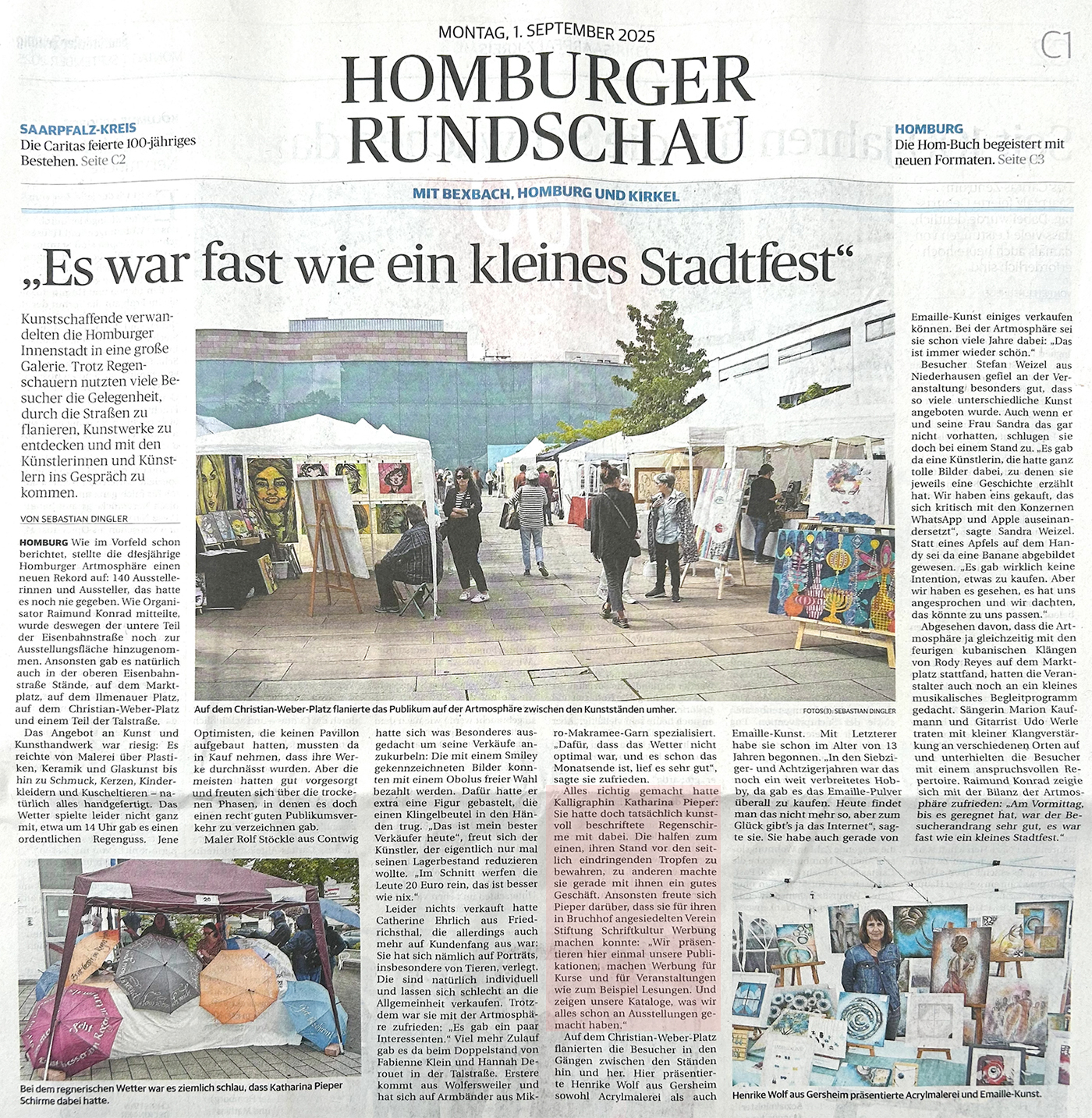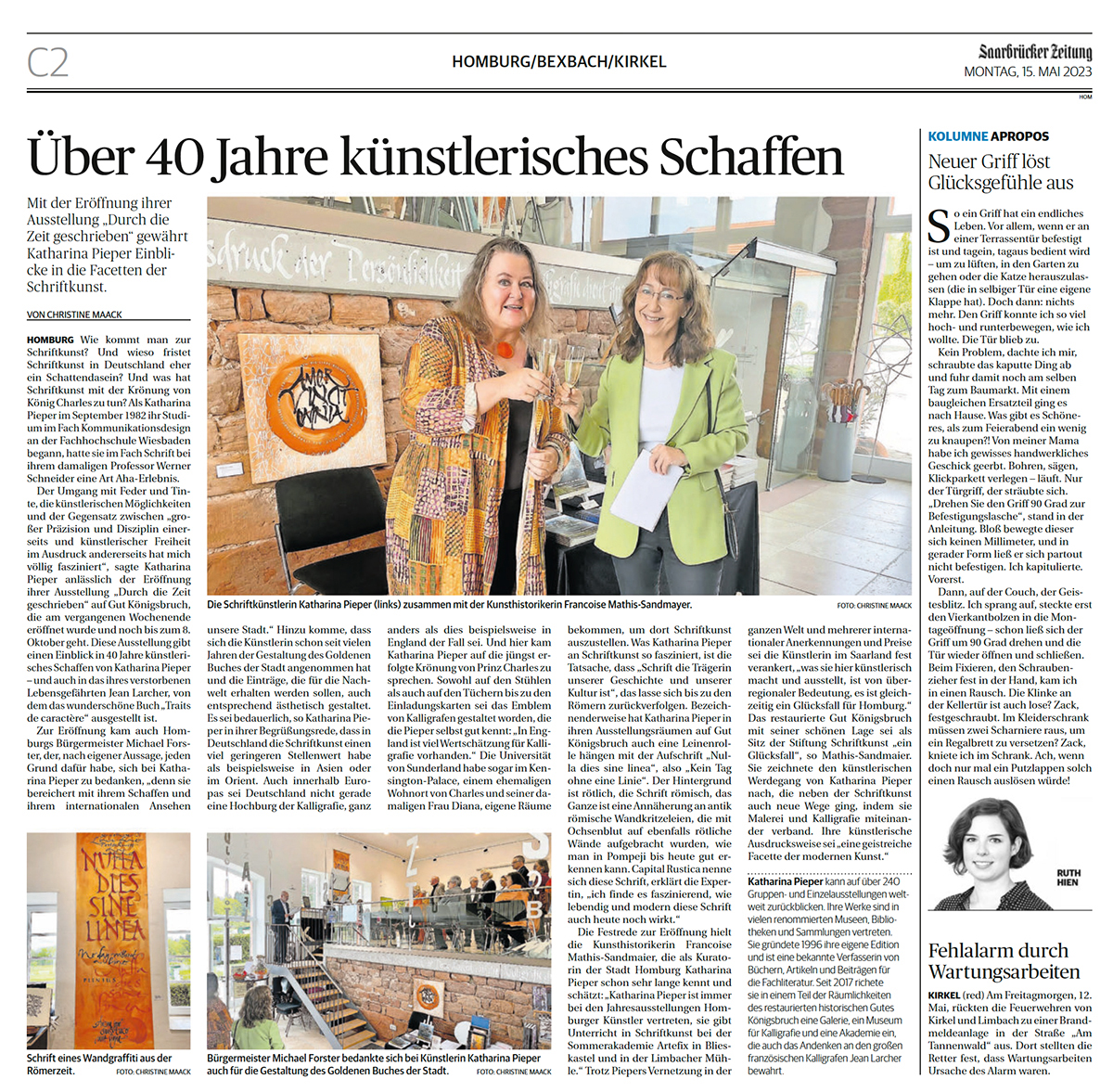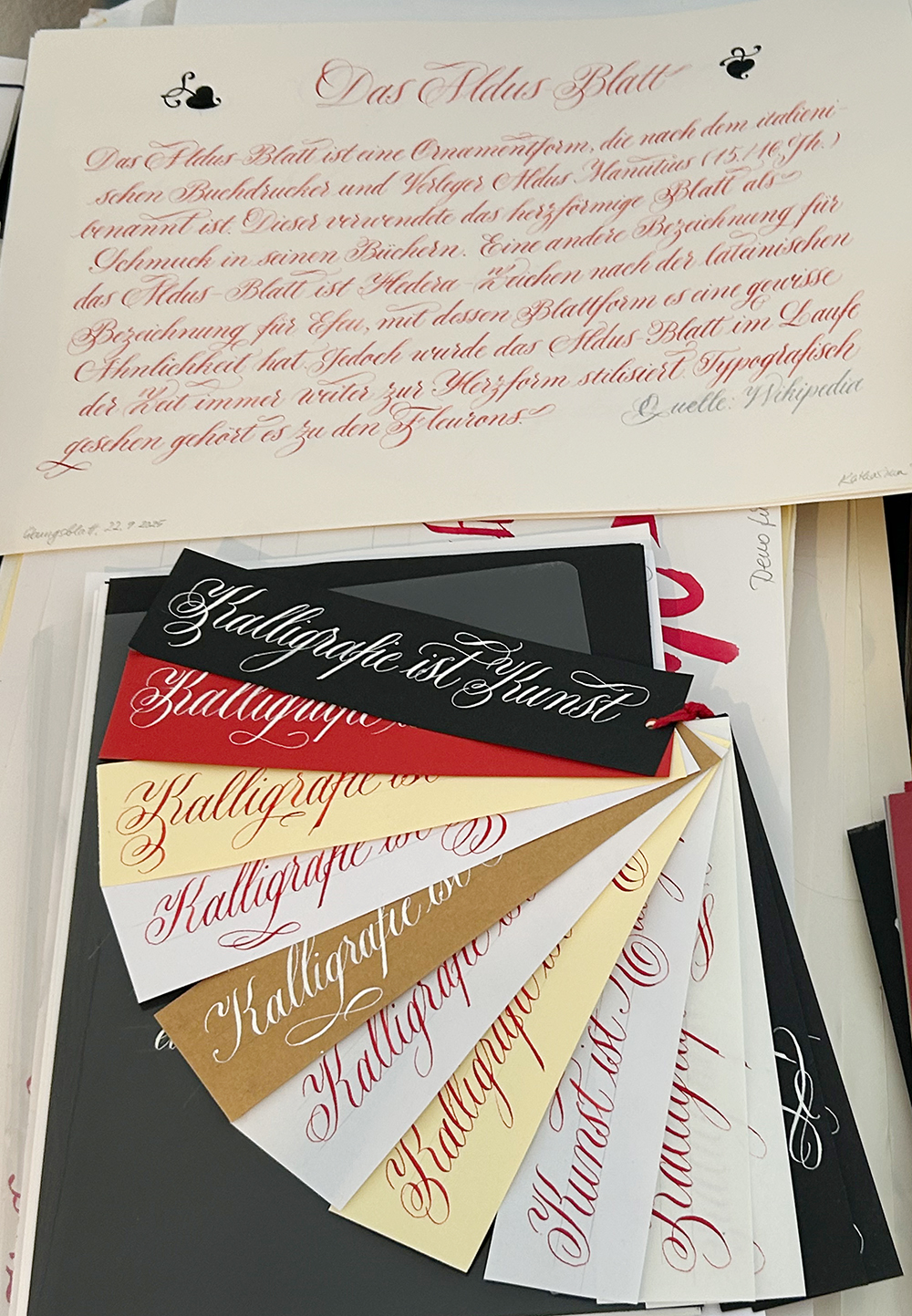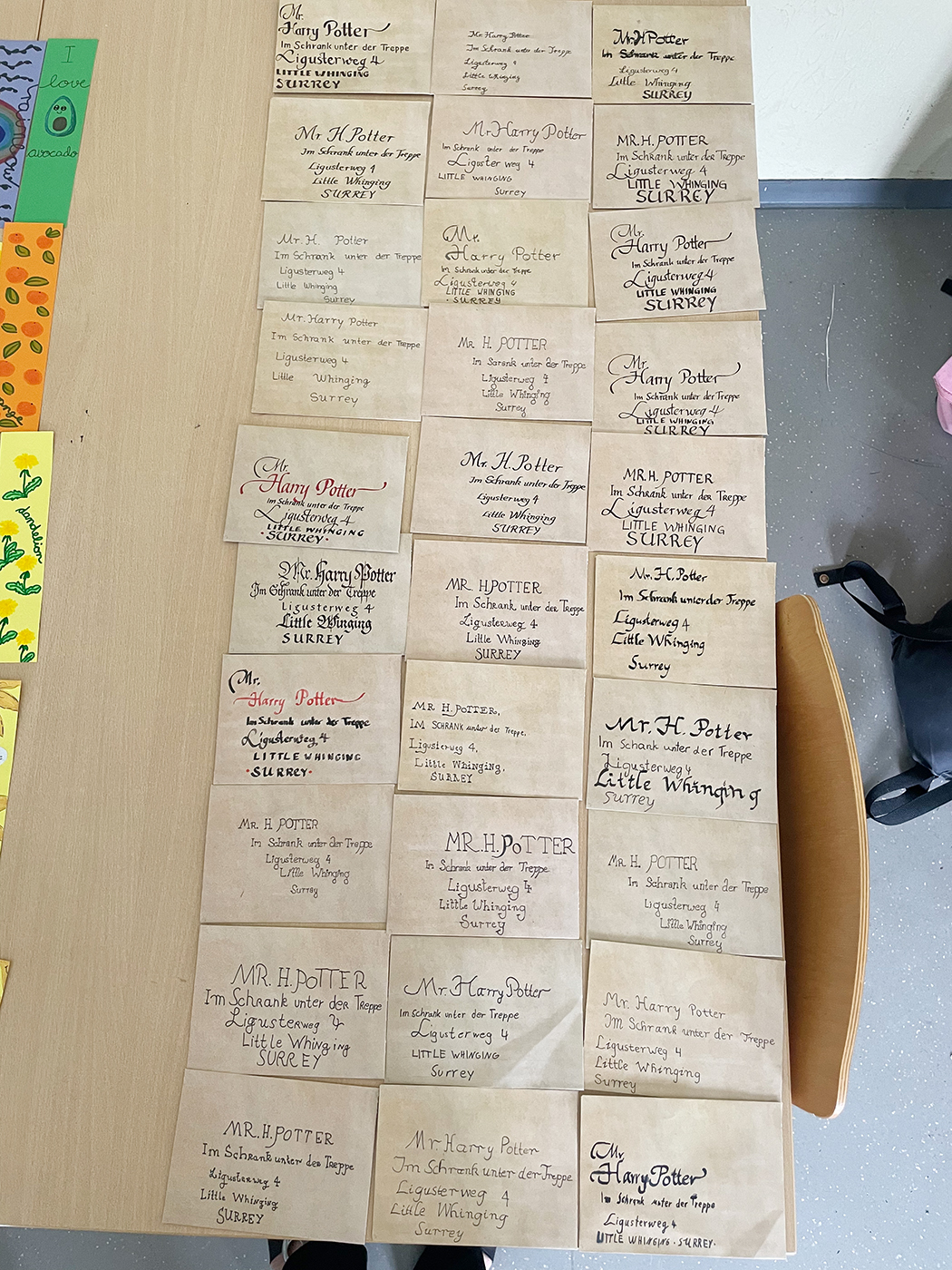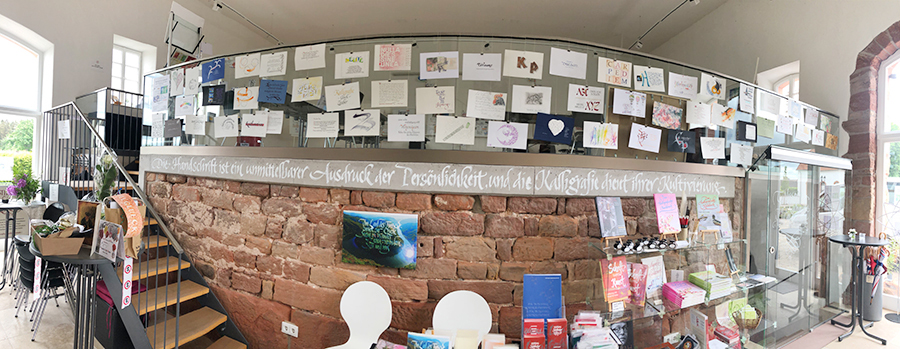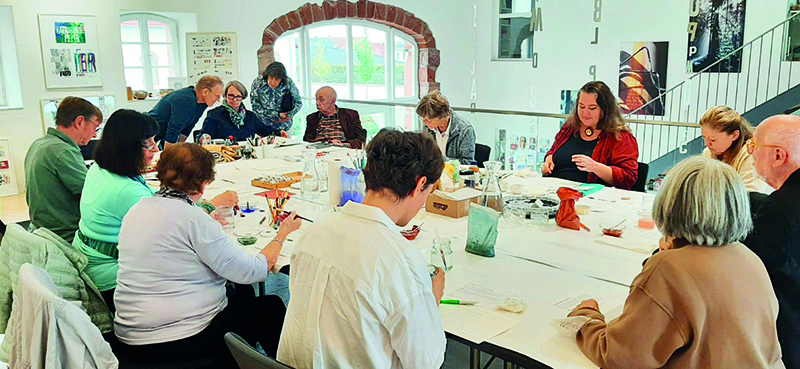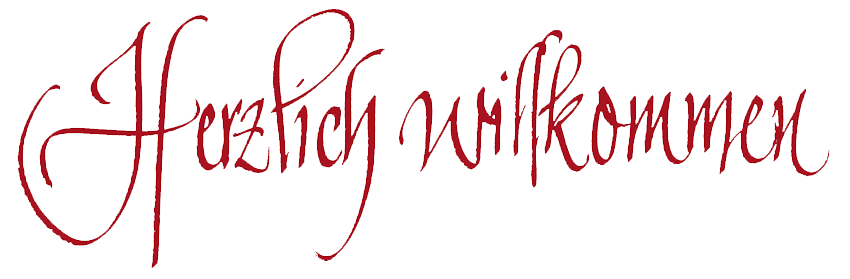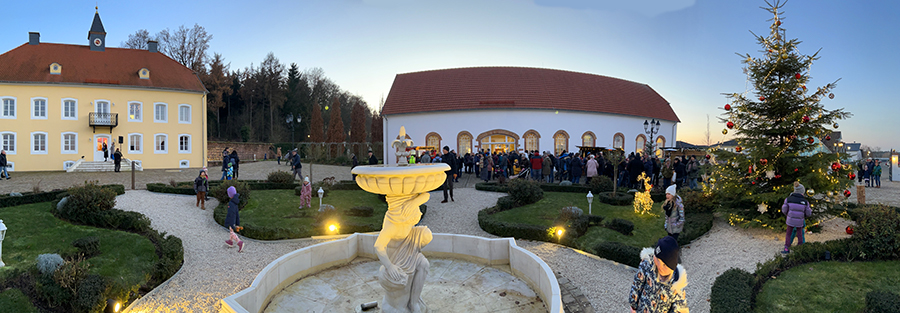
Gegründet im Juli 2016
| Der Verein Stiftung Schriftkultur e. V. wurde 2016 als gemeinnützige Einrichtung gegründet und hat seinen Sitz in Homburg (Saar). Gründerin ist die Schriftkünstlerin, Dozentin, Buchautorin und Dipl.-Designerin Katharina Pieper. Die Stiftung Schriftkultur e. V. versteht sich als eine Institution zur Förderung des Kulturgutes Schrift, der Schriftkunst, der Kalligrafie und der Typografie sowie der Handschrift als Kommunikationsmittel und als Kunstform. Wir organisieren Workshops, Kurse, Seminare und Vorträge, fördern Publikationen und Ausstellungen der Schriftkunst und der Kalligrafie und tauschen uns mit Schriftkünstlern aus aller Welt aus. Wichtig ist der Stiftung Schriftkultur auch, mit Künstlern, Sammlern, Museen, Bibliotheken, Hochschulen, Wissenschaftlern, Gesellschaften und Vereinen in einen Dialog zu treten. Im historischen Gut Königsbruch bei Homburg/Saar, 1766 von Herzog Christian IV. zu Pfalz-Zweibrücken erbaut und von privater Hand aufwendig saniert, hat die Stiftung Schriftkultur e. V. einen passenden Ort gefunden, der eine Galerie, Workshopräume, eine Bibliothek, ein Museum und das Jean-Larcher-Archiv beherbergt. Seit dem Einzug im Frühjahr 2017 finden Workshops, Führungen und Vorträge statt. Im Mai 2018 wurden die Räume mit einer Ausstellung von Katharina Pieper und Jean Larcher eröffnet. Die Stiftung Schriftkultur ist Mitglied im Saarländischen Museumsverband SMV. |
01.06.2026 Das Wochenende vom 30. und 31. Mai stand ganz im Zeichen der Humanistischen Kursive. Sieben Einsteigerinnen und ein Einsteiger widmeten sich unter fachkundiger Anleitung von Katharina Pieper der schönen und eleganten Kursive. Mit Bandzugfeder und viel Elan wurden zunächst die Kleinbuchstaben Schritt für Schritt erarbeitet, bevor es an die neue Formenwelt der Großbuchstaben ging. Alle waren mit viel Begeisterung und Arbeitseifer dabei. Zum Mittagessen brachte jeder etwas Selbstgemachtes mit – dieses Mal ganz besonders feine Delikatessen! Als kleine Abschlussarbeit gestaltete jeder ein Leporello mit einer Zeile eines kurzen Textes. Auf die am Ende präsentierten Ergebnisse waren alle sehr stolz – sie konnten sic wirklich sehen lassen, und das nach nur zwei Tagen Workshop. Vielleicht trug die große Hitze in der Galerie in diesen Tagen dazu bei, dass das Feuer des kalligrafischen Gefechts entfacht wurde und die Feder ihren Tanz über das Papier noch intensiver ausübte! |
01.05.2026 Zwei Tage nach der Ausstellungseröffnung "Im Herz des Friedens – kalligrafische Meditationen" fand in der Galerie der Tag der Kalligrafie für Kinder statt. Von nah, aber auch von fern – aus Saarbrücken, Saarlouis und Kaiserslautern – kamen Familien mit Kindern zwischen 9 und 13 jahren. Die älteste Teilnehmerin war sogar schon 18. Am Start waren Billa, Eveline, Ilse, Brigitte und Katharina, um verschiedene kalligrafische Techniken zu zeigen, aber auch, um die Kinder in ihrer eigenen Kreativität zu unterstützen. Anregung fanden die jungen Teilnehmerinnen und Teilnehmer auf den Tischen, die mit bestens vorbereiteten Werkstücken, Buchstabenbeispielen und Materialien bedeckt waren: Zeichnungen und Aquarelle mit Buchstaben, Papiere aller Art zum Beschreiben und zum Falzen kleiner Briefe, Aufkleber, Washi-Tape, Filz- und Buntstifte, Lettering Pens, Federn und vieles mehr. Nach so manch anfänglichem Zögern wurden die Kinder und auch der ein oder andere Erwachsene immer kreativer, ließ sich gerne in die Geheimnisse des Schönen Schreibens einweihen, und zum Schluss verließen alle die Stiftung Schriftkultur mit einem strahlenden Lächeln im Gesicht! |
28.04.2026 Die Ausstellungseröffnung der Ausstellung "Im Herz des Friedens – kalligrafische Meditationen" am vergangenen Freitag war wunderbar und sehr beglückend. Die Ansprachen von Katharina Pieper und Dr. Irene Özbek läuteten den Abend ein. K. Pieper trug einige Hintergründe zur Entstehung der Ausstellung, den Fotografien von Dr. Irene Özbek und von ihr selbst zu den buddhistischen Inhalten der Ausstellung und ihren Kalligrafien vor. Irene Özbek erläuterte Wissenswertes zum Buddhismus und zur Achtsamkeit, und Lama Konchok Samten, Klostervorsteher des Klosters Tinmosgang in Ladakh/Nordindien kam mit vier Mitbrüdern. Sie ließen uns an einem meditativen Gebet und Obertongesängen lauschen, was für alle Anwesenden sehr intensiv war und direkt ins Herz ging. Zum Schluss erklärte Lama Samten, der exzellent Deutsch spricht, Hintergründiges zum Selbst und dem Menschen in der Gesellschaft. Er überreichte Irene Özbek und Katharina Pieper einen farblich passenden Seidenschal als Geschenk. Zur Ausstellung erschien ein Kalender mit den ausgestellten Arbeiten, der im Gut Königsbruch zu erwerben ist. Die Hälfte der Einnahmen aus dem Verkauf des Kalenders gehen an das Waisenhaus, das an das Kloster in Ladakh angeschlossen ist und das von Lama Samten unterstützt wird. (weitere Fotos von der Geldübergabe an Lama Samten: hier, siehe 29.04.26) Der Abend klang mit guten Gesprächen und in beseelter Stimmung aus. Einen herzlichen Dank an alle Beteiligten! Zum Nachlesen: Rede von Katharina Pieper HIER, Rede von Dr. Irene Özbek: HIER |
30.03.2026 Der gestrige Tag der Kalligrafie war eine tolle Veranstaltung! Um die 100 Besucher kamen, um die schöne Atmosphäre in den Räumen der Stiftung Schriftkultur zu genießen und Brigitte Jenner, Pia Paul und Ilse Spies beim Kaligrafieren über die Schulter zu schauen. Ilse Spies zeigte Lesezeichen, Karten und viele kleine Originale und begeisterte die Zuschauer, Brigitte Jenner führte das Zeichnen historischer Buch-Ornamente auf Ostereiern vor und bot schöne Karten und Objekte an, und Pia Paul zeigte nicht nur Schrift auf Schiefertafeln, Trauerkarten oder kalligrafische Originale, sondern schrieb unermüdlich Namen für Kinder und Erwachsene. Volker Köhl hatte wieder neben edlen und handwerklich wunderbar gefertigten Füllern und Federhaltern auch allerlei neue Objekte im Angebot. Zum ersten Mal dabei war Karin Schwarz mit ihrem Mann und einer Auswahl ihres Geschäfts "Karins Lädsche" in Rieschweiler-Mühlbach. Ihrem ganz besonderen Angebot an Stempeln, Prägegerätschaften, Tinten oder Papieren konnte niemand widerstehen! Die Besucher, unter ihnen auch zahlreiche Mitglieder, kamen aus Saarlouis, Mandelbachtal, Pirmasens, Mannheim, Mainz oder Ludwigsburg - wie Familie Jenner auf dem Gruppenfoto. In zahlreichen Gesprächen entstanden auch viele gute Ideen für zukünftige Projekte! |
21.03.2026 Am 7. März fand wieder ein Einsteiger-Tageskurs unter der Leitung von Ilse Spies statt. Von einigen Teilnehmern rückte fast die ganze Familie an! So wurden unter der schwungvollen und fachkundigen Leitung der Dozentin Bandzugfedern, Redisfedern und Spitzfedern kennengelernt, verschiedene Tinten und andere Schreibflüssigkeiten wie Holzbeize oder Walnusstinte erprobt und eine einfache Schrift geschrieben. Wir freuten uns insbesondere über die große Anzahl an jungen Teilnehmer:innen, die mit viel Freude ihre ersten kalligrafischen Experimente machten. Am Ende des Tages war das einhellige Urteil, dass es ein toller Kurs war, der sehr viel Spaß gemacht hat. Eine kleine Abschlusspräsentation, in der die Teilnehmer:innen ihre besten Übungen zeigten, machte deutlich, dass schon an einem Tag der Einstieg ins künstlerische Schreiben gelungen ist. Bis schöne, größere kalligrafische Blätter entstehen können, müssen aber noch einige Kilometer geschrieben werden... Bis zum nächsten Kurs – wir freuen uns darauf! |
02.03.2026 Das vergangene Wochenende stand ganz im Zeichen des Buchbindens. Unter der Leitung von Sascha Boßlet wurde das Thema "Freie Heftungen und japanische Buchbindetechniken" erlebt und bearbeitet. Eine lebenslustige und handwerklich versierte Gruppe Pfälzerinnen, die unser Mitglied Pia Paul aus ihren Kalligrafiekursen in Karins Lädsche in Rieschweiler "mitgebracht" hat, lauschte zunächst den fachlichen Ausführungen von Sascha Boßlet zum Thema "Papier" und "Buch" ganz allgemein, da für einige das Thema neu war. Doch schnell wurden die wunderschönen und teils nicht mehr zu bekommenden Papiere aus Saschas Geschäft inspiziert und mit ihnen kleine Bücher in den praktischen, einfachen Buchbindetechniken gestaltet. Es wurde genäht, geschnitten, gefalzt, geklebt, durchstochen und gehämmert. Auf jede Frage hatte Sascha Boßlet eine kompetente Antwort parat und mit dem richtigen Utensil den passenden Tipp. Buchbinder Martin Grieser, der jahrzehntelang in der Limbacher Mühle die Buchbindekurse geleitet hat, besuchte den Kurs an einem Vormittag. Da untätig herumstehen nicht seine Sache ist, half er zur Freude der Teilnehmerinnen mit Tipps und Fachwissen aus. Am Ende wurde eine große Anzahl origineller Buchobjekte mit sehr kreativen Einbänden in einer kleinen Abschlussausstellung präsentiert – bis hin zu einem Objekt mit einem Birkenrindeeinband von Pia Paul. Kaum zu glauben, was innerhalb von nur zwei Tagen entstehen kann! |
17.02.2026 Das vergangene Wochenende stand im Zeichen der Kurrentschriften, der deutschen Schrift und der Sütterlin-Schrift. Mit viel Elan und Arbeitseifer wurden mittels feinen Bandzugfedern, Spitzfedern, der Bremer Börsenfeder oder der Rustica-Feder verschiedene Alphabete der gebrochenen Handschriften eingeübt. Dozentin Brigitte Jenner zeigte zahlreiche eigene Arbeitsbeispiele und führte unermüdlich Schriftbeispiele vor. Bei guter und ruhiger Kursatmosphäre entstanden am Ende des kurses kleine Schriftblätter mit Texten, die auch mit Metallicfarben auf schwarzes Papier geschrieben wurden. Jede Teilnehmerin bekam eine edle kleine schwarze Dose, auf die ein schwarzes Band mit kalligrafiertem Text aufgebracht wurde. Wie immer kam auch das leibliche Wohl nicht zu kurz, und allein vier Kuchen und eine riesige Packung "Mohrenköpfe" (Schaumküsse...) aus der Pfalz erfüllten mehr als reichlich den Wunsch nach Süßem! |
25.01.2026 Am 23. Januar findet alljährlich der internationale Tag der Handschrift statt. Die Wahl des Datums fiel aufgrund des Geburtstags von John Hancock auf den 23. Januar. Hancock war der dritte US-amerikanische Präsident und Mitunterzeichner der Unabhängigkeitserklärung. Auf dieser nahm seine Unterschrift ganze 13 Zentimeter ein, weshalb sein Name fortan in den USA zum Synonym für Unterschrift wurde. Um jemanden um seine Unterschrift zu bitten, kann dort also gesagt werden: "Please, put your John Hancock here!“. Wir kennen diesen Satz auch im Deutschen: „Bitte setz hier Deinen Kaiser Wilhelm hin“ als Synonym für „Unterschreibe hier handschriftlich“. Wer mehr darüber lesen möchte, dem sei dieser Bericht von Katharina Pieper – ein Brief vom 23. Januar an die Mitglieder der Stiftung Schriftkultur – ans Herz gelegt, der HIER gelesen werden kann – oder einfach auf die Bilder klicken. Obige Infografiken wurden von Axel Uhle mithilfe der KI
20.01.2026 Kurz vor dem Weihnachtsmarkt 2025 fand in der Stiftung Schriftkultur der Workshop "Enso – der Kreis ist das Ziel" mit Dr. Irene Özbek statt. Hier ein kleiner nachträglicher Bericht: ENSO bedeutet Kreis im Japanischen. Als Symbol ist ENSO eine der geläufigsten Zeichnungen der japanischen Kalligraphie, die, befruchtet durch die Geisteshaltung des Zen-Buddhismus im ENSO, die Verbindung zwischen der Einzigkeit des Augenblicks und der Vollkommenheit des Seins an sich auslotet. Zum Tagesworkshops traf sich ein (durch diverse kurzfristige Abmeldungen) sehr kleiner Kreis an Teilnehmerinnen. Zu Beginn gab Irene Özbek eine Einführung ins Thema, und die Grundthemen wurden erarbeitet. Es folgten kalligraphische Übungen, die durch Meditationen ergänzt wurden. Mittels weicher chinesischer Pinsel auf Hanf- bzw. Kozo-Papieren flossen Bewegungen und Reflexionen geschmeidig in Kreisform aufs Papier und ergaben immer ein vollkommenes, in sich abgeschlossenes Kreis-Bild. Irene demonstrierte in der Mittagspause eine Tee-Zeremonie und gab viel von ihrem immensen Wissen in Bezug auf asiatische (Heil-)Kunst preis. Es war ein sehr schöner Workshop, in dem auch viel Persönliches zur Sprache kam. Danke, Irene! |
21.12.2025 Am Nikolaustag, dem 6. Dezember, war unser Weihnachtsmarkt in der Stiftung Schriftkultur am Gut Königsbruch. Viele Besucher kamen von nah und fern, unser schönes Angebot hat sich herumgesprochen! Nicht nur die Stände mit dem kalligrafischen Angebot (Brigitte Jenner, Helga Freyer, Ilse Spies, Michaela Rayer, Regina Seiler und Katharina Pieper), auch die Füller, Federhalter und Tinten von Volker Köhl (Pen Paradise), das Angebot von Sascha Boßlet (Papier, Buchbindematerialien etc.), die handgeschöpften Papiere und Pulpemalerei von Karin Karrenbauer-Müller und die besonderen Kunst-Bücher von Bernd Detsch (Artbook Saar) wurden bewundert. Zum ersten Mal hatten wir im Museum im Gewölbekeller eine kleine Druckwerkstatt mit alten Prägeklischees, und die Besucher konnten ich davon Postkarten drucken lassen. Antonia Missy mit der Unterstützung von Sascha und Leon Boßlet druckte unermüdlich den ganzen Tag, so dass der Geruch von Druckerfarbe durch das Museum strömte. Ein rundum gelungener Weihnachtsmarkt! Danke auch an Gisela, Eveline, Helga, Sabine und Billa! |
28.11.2025 Am 19.11.25 wurde in der Sendung "Wir im Saarland – Kultur" ein Bericht über Birgit Herold, Autorin des Buches "Die Schreiberin" ausgestrahlt. Katharina Pieper hat darin kalligrafisch mitgewirkt und sich zuvor in die Handschrift der mittelalterlichen Schreiberin Clara Hätzlerin, eine Kanzleibastarda, eingearbeitet. Die Dreharbeiten fanden eine Woche zuvor in der Bibliothek der Stiftung Schriftkultur statt und haben unter der Regie von Roswitha Böhm mit ihrem Kamerateam viel Spaß gemacht. Birgit Herold war sehr berührt, dass die Hauptdarstellerin ihres Buches durch die schreibende Hand von Katharina Pieper sozusagen wieder zum Leben erweckt wurde. Der Bericht ist in der SR-Mediathek unter diesem Link zu sehen: H I E R Der Beitrag kann einzeln angeklickt werden (4. von links), ebenso kann die komplette Sendung mit der Ansage von Verena Sierra angeschaut werden. Den Schluss der Sendung ansehen!!! |
01.11.2025 Am 28. August besuchte der SR die Stiftung Schriftkultur. Barbara Lindahl und Kameramann Alex drehten einen Bericht über die Arbeit von Katharina Pieper und ihren Unterricht von Erwachsenen und Kindern. Am gestrigen 31. Oktober wurde der Bericht in der Sendung "Wir im Saarland – Saar nur" ausgestrahlt. In der Mediathek des Saarländischen Rundfunks kann die Sendung unter diesem Link angesehen werden. Ab der 17. Minute beginnt der Fernsehbericht, der in der Vorankündigung unter unter dem Titel "Verzaubert von schöner Schrift" angekündigt wurde. HIER GEHTS ZUR MEDIATHEK UND DER SENDUNG. |
10.10.2025 Das Buch "Die Schreiberin" mit dem Untertitel "Federn, Tinte, geheime Lettern – eine Frau schreibt Geschichte" von Birgit Herold wurde am gestrigen Abend einer großem Gruppe interessierter Zuhörer von der Autorin vorgestellt und im stimmungsvollen Ambiente präsentiert. Frau Herold und ihr Mann brachten zahlreiche Utensilien mit, die den Inhalt des Buches passend illustriert haben: Kerzen, Gänsekielfedern und Eisengallustinte, die aus Galläpfeln hergestellt wird, Bücher, die das Leben im Mittelalter beschrieben und weitere authentische Gegenstände. Gespannt lauschten die Anwesenden Frau Herold beim Lesen einiger Auszüge aus ihrem Buch zu und stellten zahlreiche Fragen. Das Leben der Schreiberin Clara Hetzlerin, die im 15. Jahrhundert in Augsburg gelebt hat, wurde an diesem Abend und im Buch von Birgit Herold aufs Treffendste zum Leben erweckt. Eine spannende Empfehlung! Birgit Herold hat auf ihrer Instagram-Seite auch einen wunderbaren Bericht gepostet: https://www.instagram.com/p/DPnu35tDNHr/?img_index=1 |
06.10.2025 Am gestrigen Tag der Kalligrafie führten Katharina Pieper, Brigitte Jenner, Michaela Rayer, Ilse Spies und Volker Köhl Kalligrafisches und Handwerkliches rund um die Schöne Schrift vor. Zahlreiche interessierte Besucher stellten Fragen und schauten uns über die Schulter. Es ergaben sich gute Gespräche und Kontakte. Namen in englischer Schreibschrift wurden geschrieben, Blätter in Bastarda vorgeführt. Karten und Lesezeichen hergestellt, zahlreiche Federtypen und Techniken des Schreibens gezeigt, Embossings erstellt, Namen auf Schreibwerkzeuge graviert und viele kalligrafische Werke gezeigt. Judith aus Saarbrücken und Irina aus Ingelheim, zwei begeisterte Mitglieder der Stiftung Schriftkultur, halfen beim Zählen der Besucher und warben mit viel Charme für unsere Bücher, Kataloge und die Kalligrafie. Schön war's! |
28.09.2025 Der gestrige Samstag stand wieder einmal unter dem Thema "englische Schreibschrift". Die Teilnehmerinnen vertieften sich unter der Leitung von Katharina Pieper in die elegante und nicht leicht zu schreibende Schrift. Die Materialien, die für diesen Kurs notwendig sind – spezielle feine und elastische Spitzfedern, ein mit Schriftlinien und Schrägen vorgezeichneter Schreibblock, Layoutpapier, Gouache oder Oblique-Federhalter – werden von Katharina Pieper extra für die Kurse bestellt oder in Spezialgeschäften erworben. Einzelworte, Zeilen und verschiedenen Schriftgrößen standen neben den Klein- und Großbuchstaben mit besonderen Schwüngen an diesem Tag auf dem Programm. Rechts: Teilnehmerin Sabine hält ein bekanntes, von Jean Larcher gestaltetes Plakat – sie hatte gestern Geburtstag! |
10.09.2025 Am gestrigen Dienstag fand zum 8. Mal die Pressekonferenz der Kammermusikfreunde in den Räumen der Stiftung Schriftkultur e. V. statt. Stefan Fehland (Berlin/Stuttgart), Professor für Viola und Mitglied des bekannten Vogler Quartetts, stellte das Programm der diesjährigen Kammermusiktage vor, die vom 27. September bis zum 3. Oktober 2025 in Homburg stattfinden. In Anbetracht der Tatsache, dass das Quartett vor genau 40 Jahren gegründet wurde, gab Stefan Fehland auch viele Hintergründe und Anekdoten aus dieser langen gemeinsamen Zeit zum Besten. Der Vorstand der Kammermusikfreunde unter dem Vorsitz von Dr. Gudula Zimper bedankte sich bei Katharina Pieper herzlich für die Gastfreundschaft. |
09.09.2025 Am Stand auf dem Künstlermarkt ARTmosphäre, die am 30. August 2025 stattfand, zeigte Katharina Pieper nicht nur eigene Arbeiten, sondern präsentierte auch die Stiftung Schriftkultur. Die ARTmosphäre bot alles: vom strahlenden Sonnenschein bis zum strömenden Regen. Bücher, Karten und Kataloge wurden durchweicht, doch die Original-Kalligrafien konnten gerettet werden, auch dank Michaela und Billa. Katharina Pieper fertigte im Vorfeld des Künstlermarktes zahlreiche Schirme mit kalligrafischer Beschriftung an, und auch am Nachmittag zeigte sie mit einem einfachen wasserfesten Filzstift, wie ein Schirm beschriftet werden kann. Die Performance kam gut an, und zahlreiche Texte zum Thema Regen und Wasser fanden einen neuen Platz auf den weißen Schirmen. Insbesondere die Mitglieder der Stiftung Schriftkultur freuten sich über die Begegnungen und die kalligrafische Vorführung. In der Saarbrücker Zeitung fanden wir anschließend Erwähnung wegen der passend in Szene gesetzten Schirme (auf das Foto klicken)! Danke Michaela, Billa und Martin für die tatkräftige Hilfe! |
28.08. 2025 Gestern besuchte der SR die Stiftung Schriftkultur. Für die Sendung "Wir im Saarland – SaarNur" drehten Barbara Lindahl und Kameramann Alex den ganzen Tag eine Doku über das Schreiben und Kalligrafieren. Zum Schulanfang soll auf den Wert der handgeschriebenen Schrift hingewiesen werden. Die 13-jährigen Schüler Hannah und Milian wurden zu "Filmstars" und konnten ihre Kenntnis der Kalligrafie unter Beweis stellen und zeigen, was sie am Saarpfalz-Gymnasium bei Lehrerin Christine Wack gelernt haben. Drei langjährige Kursteilnehmerinnen von Katharina Pieper wurden ebenfalls interviewt und deren Arbeiten gefilmt. Nicht zuletzt wurden zahlreiche Sequenzen mit Katharina Pieper beim Kalligrafieren gedreht und einige Fragen gestellt. Es hat allen großen Spaß gemacht, und wir freuen uns auf den Bericht! |
| Vom 14.bis 18. Juli 2025 fand die Woche der Kalligrafie für Fortgeschrittene an der saarländischen Sommerakademie in Blieskastel mit Katharina Pieper statt. Das Thema war eine Kalligrafie aus Jean Larchers Buch "Traits de Caractère – Linien mit Charakter" mit dem Satz von Napoleon "Ein Bild sagt mehr als tausend Worte.". Es handelt sich um eine personalisierte Kursive, und aufgrund des Autors gab K. Pieper dieser Schrift den Namen "Napoleon". Sie entwarf alle fehlenden Buchstaben des Alphabets, und die Teilnehmerinnen lernten diese Buchstaben. Nach vielen speziellen Übungen wurden Texte geschrieben. Am Schluss des Kurses erhielt jede Teilnehmerin einen Druckbogen von Jean Larchers Buch, so dass ein Leporello (Faltbuch) hergestellt werden konnte. Zur Abrundung wurde die noch laufende Ausstellung "Hommage an jean Larcher" in der Stiftung Schriftkultur im Gut Königsbruch besucht. Eine schöne und intensive Woche war es! |
28.06.2025 Am vergangenen Wochenende fand wieder unser Kalligrafie-Tag für Kinder statt. Obwohl, auch hitzebedingt, nur wenige Kinder zu uns kamen, wurde fleißig kalligrafiert, gelettert, geschnitten, gefalzt, gezeichnet, gestempelt und geprägt. Diejenigen, die gekommen sind, waren sehr interessiert und haben die ganze Zeit fleißig geschrieben und ausprobiert. Eine junge Journalistin der Rheinpfalz setzte sich nach dem Interview mit Katharina Pieper sogar dazu und nahm die Bandzugfeder in die Hand. Dabei stellte sich heraus, dass sie Vorerfahrung in humanistischer Kursive hatte. Brigitte zeichnete mit den Eltern dekorative Initialen, Volker nahm die ganz Kleinen unter seine Fittiche und brachte ihnen viel bei. Eveline war zum ersten Mal dabei und bereitete einiges im Vorfeld für die Kinder vor, und Katharina zeigte bunte Handlettering- Ideen sowie Kalligrafisches mit der Feder. Danke an alle, auch an Christine, die die Ankömmlinge betreute. |
06.05.2025 Am ersten Sonntag im Mai fand wieder ein Tag der Kalligrafie in unserer Galerie statt. Viele interessierte Besucher von nah und fern kamen zu uns, um sich über unsere Aktivitäten zu erkundigen. Viele, die zum ersten Mal da waren, waren – wie immer – beeindruckt, auch von den großzügigen Räumen der Stiftung Schriftkultur und vom gesamten Anwesen Gut Königsbruch. Inmitten der derzeit laufenden Ausstellung "Hommage an Jean Larcher" führte Katharina Pieper verschiedene Schriften vor, und wer wollte, konnte sich nicht nur ein Lesezeichen mit dem eigenen Namen schreiben lassen, sondern auch Glasfedern, handgefertigte Bambusfedern oder Bierdosenfedern erwerben. Brigitte Jenner und Ilse Spies zeigten diverse kalligrafische Techniken auf edlen Papieren und boten schöne handgeschriebene Karten, Leporellos, Büchlein und vieles mehr zum Verkauf an. Volker Köhl gravierte Namen oder andere Schriftzüge auf verschiedene Schreibgeräte oder weitere praktische Utensilien. Auch die Kinder freuten sich über seine humorvolle Art und lernten manches technische Fachwissen. Es war ein voller Tag mit vielen guten Gesprächen, und bei dem ein oder anderen wurde das Interesse für weitere Besuche geweckt. |
06.04.2025 Unser Tag für Kinder fiel in diesem Jahr wohl auf einen Tag, an dem viele Veranstaltungen stattfanden. Daher kamen nur sehr wenige Kinder zu uns, um bei Brigitte Jenner, Sascha Boßlet, Michaela Rayer, Volker Köhl und Katharina Pieper Spannendes rund um die Kalligrafie und das Papier zu lernen. Zeichnen von Initialen, Herstellung von Siegeln auf Briefen, die zuvor selbst hergestellt wurden, die Anwendung von besonderen Zeichenschablonen, die mit Buchstaben verknüpft wurden, und natürlich die Kalligrafie mit Bandzugfeder wurden mit Freude und Passion gezeigt und geübt. Auch Christine und Regina waren wieder treue Helferinnen an der Kasse und in der Küche. Die Erwachsenen setzten sich später ebenfalls an die "Kindertische", um die schönen Techniken anzuwenden. Zum Lernen ist es nie zu spät! – In der Werkstatt von Volker Köhl konnte eine kleine Gruppe von Interessierten am vergangenen Freitag sehen, wie ein Federhalter an der Werkbank entsteht, später poliert wird und schließlich der Einsatz zum Halten der Feder eingefügt wurde. Ein langwieriger Prozess, der viel Wissen und Können erfordert. Volker Köhl stellte im Anschluss Füller, Tinten und Papiere vor, die das Herz jedes Kalligrafen höher schlagen lassen! Danke, Volker! |
26.03.2025 Am vergangenen Wochenende fand wieder ein Kurs zum Thema "Englische Schreibschrift" (Anglaise) mit Katharina Pieper statt. Die eleganten und auch richtig schwierigen Großbuchstaben standen in diesen Tagen auf dem Programm. Grundformen der Buchstaben, Schwünge und "Schnörkel" wurden nicht nur mit Bleistift, sondern auch mit verschiedenen Spitzfedern geübt, wobei jede Teilnehmerin ihre eigene Lieblingsfeder getestet und für gut befunden hat. Hervorragende Vorlagen, die der Spezialist für Englische Schreibschrift Jean Larcher geschrieben hatte, dienten als Anschauungs- und Studienobjekte. Die Dozentin zeigte zahlreiche Varianten der Buchstaben, und zum Schluss wurden einige Blätter auf schwarzem Papier mit weißer und roter Gouache gestaltet. Auf dem Foto rechts sieht man die stolzen Teilnehmerinnen, die ich über ihre Blätter freuen! Wie immer kam das leibliche Wohl nicht zu kurz, und in den Mittagspausen wurden feine selbstgemachte Salate, Brotaufstriche und Kuchen verzehrt. Ein Kurs mit viel Know-How! |
09.03.2025 Am gestrigen Samstag fand in der Galerie der Tageskurs "Feder, Tinte und Papier – Einstieg ins Schöne Schreiben" mit Ilse Spies statt. Bei herrlichem Sonnenschein lernten die Teilnehmerinnen und Telnehmer, mit Bandzug-, Redis- und Spitzfeder umzugehen und ihre Handschrift sowie einfache Alphabete ins rechte Licht zu rücken. Mit viel Elan zeigte die Kursleiterin eigene Beispiele, Karten und viele Möglichkeiten der Anwendung. Die jungen und junggebliebenen Teilnehmer waren nicht nur vom Kurs, sondern auch vom Ambiente unserer Räume begeistert. – Auch das offene Atelier findet seit Mitte Februar wieder in unserer Bibliothek statt. Derzeit wird fleißig englische Schreibschrift geübt. Beim letzten Mal wurden mit dieser schönen, eleganten Schrift kalligrafische Briefumschläge gestaltet. Dabei dienen nicht nur Umschläge von Jean Larcher als leuchtende Beispiele, sondern Katharina Pieper demonstriert auch verschiedene Möglichkeiten der Gestaltung und Anwendung. |
03.03.2025 Am gestrigen Sonntag wurde bei herrlichstem Wetter und strahlendem Sonnenschein die Ausstellung "Hommage an Jean Larcher – Kalligraf und Lettering Artist" eröffnet. Die Ausstellung zeigt einen Überblick über Jean Larchers Werk aus verschiedenen Schaffensperioden. Zum Erstaunen einiger Besucher fanden sich in der Ausstellung auch farbige Arbeiten auf Leinwand aus den Ausstellungen "Texturen des Herzens" und "Blues" wieder. Auch die Hommage an deutsche Schriftkünstler, die Jean in der Büchergilde Wiesbaden im Jahr 2011 zeigte, wurde präsentiert. Zur Eröffnung stellte Katharina Pieper zunächst die Werke und den Schriftkünstler vor und gab einige Einblicke in gemeinsame Tätigkeiten. Die Kunsthistorikerin Dr. Françoise Mathis-Sandmaier, die Jean persönlich gut kannte, hielt eine wunderbare Laudatio mit zahlreichen "jeux de mots" (Wortspielen), in der sie viele Facetten seiner Persönlichkeit beleuchtete und Jean Larcher mehr als gerecht wurden. Bei guter Stimmung wurden persönliche Gespräche geführt, manche Anekdoten erzählt und an Jean Larcher als Künstler und als Mensch gedacht.
|
Jean Larcher (1947 – 2015)
09.01.2025 Am 17. Januar 2025 jährt sich der Todestag von Jean Larcher zum 10. Mal. Diese Fotos zeigen ihn anlässlich der Ausstellung "Wenn Linien Flügel verleihen, Kalligrafien von Katharina Pieper und Jean Larcher" im Oktober 2014 im Schrift- und Heimatmuseum Pettenbach in Österreich. Info: http://www.schrift-kunst.de/Einladung_3-2014-1.pdf Jean Larcher gab in dieser Woche auch einen Kurs zur Englischen Schreibschrift – sein letzter Kurs. Auf dem rechten Foto sind Jean Larcher und K. Pieper zusammen mit Kollege Giovanni de Facchio am Abend der Ausstellung im Schriftmuseum zu sehen. Jean Larcher hat die Aktivitäten von Katharina Pieper zur Gründung der Stiftung Schriftkultur im Jahr 2016 und die Einrichtung der Räume im Gut Königsbruch nicht mehr mitbekommen. Sein Buch "Traits de Caractère – Linien mit Charakter" erschien im März 2014, somit konnte er den Erfolg noch eine kurze Zeit genießen. Jean Larcher fehlt... Seine Seele lebt in seinen Kalligrafien. |
Das war unser Weihnachtsmarkt 2024:
_______________________________________________________________________
..
12.12.24 Am 7. Dezember, dem 2. Adventssamstag, fand unser diesjähriger Weihnachtsmarkt statt. Trotz des widrigen Wetters kamen viele Besucher zum weihnachtlich geschmückten Gut Königsbruch, um die schöne Stimmung bei uns und am gesamten Hofgut zu genießen. Unsere Aussteller hatten alle ein breites Angebot, das auf großen Zuspruch traf. Im Eingangsbereich stellten die Stiftung Schriftkultur und Katharina Pieper aus, in der Galerie Sascha Boßlet mit wunderschönen Papieren und Schreib- und Buchbindebedarf, Michaela Rayer mit handgeflochtenen Tannenbäumen, Papiersternen und weiteren zauberhaften Objekten und Helga Freyer mit viel Bewährtem und Originellem. Regina Seiler zeigte ein breites Angebot rund um kalligrafische Objekte, Sigrid Goldschmidt aus Aachen stellte ihre Radierungen, Zeichnungen und Kalligrafien aus, Volker Köhl präsentierte wie immer seine handgefertigten Schreibobjekte und hatte viel Neues dabei, und Ute Müller-Eisenlohr bot Buchobjekte, Weihnachtssterne aus Papier und viele weitere Kostbarkeiten an. In der Bibliothek hatte Bernd Detsch (Art Book Saar) seinen großen Stand mit Büchern und vielen Kunstbuchraritäten, und Susanne Schmidt präsentierte ihre schönen Patchworkarbeiten mit den beliebten Federmäppchen. Auch das neue Jahrbuch 2024 stand in Umschlägen für unsere Mitglieder bereit. Alle, sowohl die Besucher als auch die Aussteller und fleißigen Helferinnen Karin, Sibylle, Eveline, Gisela und Christine freuten sich über einen gelungenen Weihnachtsmarkt! (Fotos: S. Becker, K. Fischer, K. Pieper) |
30.11.24 Der heutige Kurs "Feder, Tinte und Papier – Einstieg ins schöne Schreiben" mit Ilse Spies bringt sechs Teilnehmerinnen und Teilnehmern wieder die schöne Art, kalligrafische Schreibfedern zu nutzen und damit kleine Blätter zu gestalten, nahe. In winterlicher Kälte fanden die Dozentin und die Teilnehmer am Morgen zu uns, während im Hof schon die Vorbereitungen für den Weihnachtsmarkt auf Hochtouren laufen. Im Inneren sind die Räume schon weihnachtlich geschmückt, und viele Lichterketten und Beleuchtung zaubern eine weihnachtliche Stimmung. Wir freuen uns auf den Weihnachtsmarkt, der am kommenden Samstag, dem 7. Dezember von 11 bis 18 Uhr, stattfinden wird. Herzlich willkommen! |
30.10.24 Der Tageskurs "Leporellos und andere Faltbücher" am vergangenen Samstag brachte den Teilnehmerinnen wieder viel Neues und machte allen Spaß. Dozentin Michaela Rayer hatte eigene kleine und größere Vorbilder im Gepäck, die sehr individuell und mit wunderschönen Papieren und Stoffen eingebunden waren. Im Kurs fertigte sich jeder kleine "Dummies" als Musterfaltbücher, die später dazu dienen können, weitere eigene und auch größere Leporellos herzustellen. Der Umgang mit Papier, Falzbein, Planatol-Kleber, doppelseitigem Klebeband und vielen weiteren Materialien war für die ein oder andere Neuland, doch andere Damen besuchten bereits Buchbindekurse und kannten die Werkzeuge. Die Dozentin brachte viel Know How mit, und die Ergebnisse fielen entsprechend zur Freude der Teilnehmerinnen aus! |
23.09.24 Am vergangenen Wochenende kamen 12 Schriftbegeisterte zusammen, um am Kurs "Kalligrafische Hintergründe" mit Katharina Pieper teilzunehmen. Das schöne warme Wetter, eine begeisterte Gruppe, viel Input und ein feines Mittagsbüffet mit 4 selbstgebackenen Kuchen trugen zu einem gelungenen Kurs bei. Pastellkreide, Frottagen, Aquarell, Sprühtechnik oder Naturdrucke sind nur einige der Techniken, mit denen zahlreiche Blätter als Hintergründe für Kalligrafisches angelegt wurden. "Nach diesem Wochenende bin ich wieder aufgeladen." oder "Es hat mir so gut getan!" sind nur einige der Kommentare der Teilnehmerinnen und Teilnehmer. Es war ein Wochenende voller guter Laune, taschenweise Materialien und wunderschönen Arbeitsergebnissen! |
23.09.24 Am Mittwoch in der vergangenen Woche fand bereits zum 7. Mal die Pressekonferenz der Kammermusikfreunde in den Räumen der Stiftung Schriftkultur statt. Das musikalische Programm und die Künstler wurden vom Vorstand und Stefan Fehland, Mitglied des bekannten Vogler Quartetts, den Vertretern der Presse vorgestellt. Die Kammermusiktage im Homburger Saalbau beginnen am 26. September und gehen bis zum 3. Oktober. Das Foto auf der Treppe von Ulrike Stumm mit einem schönen Bericht war bereits am darauffolgenden Tag in der Saarbrücker Zeitung. Am Nachmittag des gleichen Tages besuchten Pia Paul und Helga Freyer die Goethe-Ausstellung, wobei dieses schöne Foto (rechts) entstand. Das mittlere Foto wurde am Donnerstag Morgen vom Fenster des Büros der Stiftung Schriftkultur gemacht: Ein strahlender Tag am Gut Königsbruch! |
01.09.24 Am gestrigen Samstag lockte der Künstlermarkt ARTmosphäre bei strahlendem Sonnenschein zahlreiche Besucher in die Homburger Innenstadt. Die Stiftung Schriftkultur war wieder mit einem Stand vertreten. Michaela Rayer und Volker Köhl (Pen Paradise) unterstützten Katharina Pieper tatkräftig und mit guter Laune. Am Nachmittag bereitete K. Pieper eine Mitmach-Performance vor. Ein Goethe-Portrait als Silhouette auf großem Papier animierte die Zuschauer, in ihrer eigenen Handschrift – wer wollte, auch in kalligrafischer Schrift – ein Gedicht oder einen Ausspruch des großen Dichters in diesen Kopf hereinzuschreiben. Haupt-Organisatorin der ARTmosphäre Dr. Françoise Mathis-Sandmaier freute sich über die gelungene Aktion, und Raimund Konrad, Kulturbeigeordneter der Stadt Homburg, stellte uns wieder seinen Pavillon zur Verfügung. Danke! (Fotos : Volker Köhl, Francoise Mathis-Sandmaier, Michaela Rayer, KP) |
22.08.24 Anfang August besuchte die Gesellschaft Ars Scribendi die Stiftung Schriftkultur und das Deutsche Zeitungsmuseum Wadgassen. Samstags gab es zwei Führungen für die Gesellschaft in der Ausstellung "Abenteuer Schrift" im Zeitungsmuseum, und Katharina Pieper zeigte auch den von ihr gestalteten Raum mit der "Kleinen Geschichte der Schrift". Der Film über K. Pieper, der in der Ausstellung angesehen werden konnte, bot weitere Informationen zu ihrer Arbeit. Nach einer Stärkung begab sich ein Teil der Gruppe in die Urban Art Biennale im Weltkulturerbe Völklinger Hütte. Am Sonntag hielt Ars Scribendi ihre Mitgliederversammlung in den Räumen der Stiftung Schriftkultur ab. Auch hier erfuhr die Gruppe anschließend vieles zur Geschichte des Hofguts und zur Entstehung und den Aktivitäten des Vereins Stiftung Schriftkultur. Ein reger und freundschaftlicher Austausch rundete das schöne gemeinsame Wochenende ab. Die Mitglieder der Gesellschaft Ars Scribendi (der Katharina Pieper von 1997 bis 2003 vorstand) kamen aus ganz Deutschland: Berlin, Hamburg, Ulm, Bayern, Bochum, Essen, Reutlingen, Frankfurt, Mannheim und vielen anderen Städten. (Fotos : Ernst, KP) |
11.07.24 Gestern kam im Rahmen einer Kalligrafie-Projektwoche eine 20-köpfige Schülergruppe des Saarpfalz-Gymnasiums unter der Leitung ihrer Lehrerin Christine Wack zu uns ins Gut Königsbruch. Frau Wack selbst ist nicht nur begeisterte Kalligrafin, sondern auch Mitglied der Stiftung Schriftkultur. Katharina Pieper führte die Gruppe, deren Teilnehmerinnen und Teilnehmer zwischen 12 und 17 Jahren alt waren, durch das Museum und die aktuelle Goethe-Ausstellung und demonstrierte im Anschluss viele Schriften und Schreibwerkzeuge. Das Schulprojekt "Brief an Harry Potter" machte allen viel Spaß, auch K. Pieper, die zwei Briefumschläge für die Schüler gestaltete. Wer kann sie zwischen den Umschlägen der Schüler entdecken? Einfach auf das Bild ganz rechts klicken, dann wird es vergrößert. Die Umschläge der Schüler sind sehr kreativ und zeigen, dass schon nach einigen Tagen Schriftunterricht schöne Ergebniosse entstehen können! (Fotos : Christine Wack) |
16.06.24 Die zweite Führung für die Stiftung Schriftkultur im Deutschen Zeitungsmuseum in der Ausstellung "Abenteuer Schrift" fand am gestrigen Samstag statt. Die Ausstellung läuft noch bis zum 25. August, anschließend wird die Wandgestaltung von Katharina Pieper wieder entfernt. Also: Noch die Gelegenheit nutzen und die kalligrafisch gestaltete "Kleine Geschichte der Schrift" mit der Installation von Werken des Schriftkünstlers Jean Larcher ansehen! – In diesem Jahr wurden die Rosen in unserem Vorgarten bisher noch nicht von Rehen gefressen! Dafür wurden die Buchsbäume, die dem Buchsbaumzünsler zum Opfer gefallen sind, durch zwei ähnliche Pflanzen, "Laurus lusitania angustifolia", ersetzt. Katharina Pieper brachte sie kürzlich aus Belgien mit. (Nachtrag am 26.06.24: Leider wurden die Rosen inzwischen doch gefressen...) (Foto DZM: Wilfried Köhn) |
02.06.24 Im Rahmen des Goethe-Jahres und der Veranstaltungsreihe "Inspiration Goethe" führten wir gestern die Veranstaltung "Schreiben wie zu Goethes Zeiten" durch und widmeten uns Gedichten und Texten von Johann Wolfgang von Goethe. Eine kleine Gruppe Interessierter erfuhr zunächst einige schriftgeschichtliche Hintergründe zur Entstehung von Kurrentschrift, Kanzleischrift, Sütterlin und deutscher Schrift sowie der Nutzung von Gänsekiel- und Stahlfeder von Katharina Pieper. Im Anschluss wurden einige Texte Goethes vorgetragen, darunter auch "Der brennende Berg von Sulzbach". Brigitte Jenner und Ilse Spies demonstrieren die Kurrentschrift mit der Spitzfeder, und wer wollte, konnte sich im Schreiben der historischen Handschrift mit Bleistift und Feder üben. Die Dozentinnen sowie eine belesene Besucherin zeigten Bücher, original handgeschriebene Briefe und einen Facsimiledruck aus ihrer Sammlung. So lebte die Kurrentschrift inmitten unserer Mitgliederausstellung „275 Jahre Johann Wolfgang von Goethe – Texte werden Schrift-Bilder“ wieder auf. Dank an Klaus Friedrich, der die Veranstaltungsreihe in Homburg und im Saarland ins Leben gerufen hat. |
30.05.2024 Die Veranstaltungen häufen sich gerade in der Stiftung Schriftkultur! Nach dem Internationalen Museumstag am 19. Mai fand der Tag der Kalligrafie am 26. Mai statt. Er verlief mit vielen Besuchern und guten, informativen und freundschaftlichen Gesprächen. Brigitte Jenner (Mitte, mit Judith M.) zeigte irisch-angelsächsische Halbunziale, Ilse Spies die Bastarda Espanola, Katharina Pieper Fraktur und freie, experimentelle Schrift mit Bierdosenfeder und Balsaholz, und Volker Köhl (Pen Paradise, Saarpen) bot seine wunderschönen handgefertigten Füller, Federhalter und andere Schreibobjekte an. Foto links: Besuch von (Kunst)Historikerin Dr. Jutta Schwan (ganz rechts) mit Gusti, der Eule vom Homburger Schlossberg – hier im Gespräch mit Katharina P., Brigitte S. und Ute S. Rechts: Am vergangenen Dienstag fand eine Fortbildungsveranstaltung des Saarländischen und Rheinland-pfälzischen Museumsverbands statt. Frau Dr. Victoria Asschenfeldt leitete Museumsleiter aus dem gesamten Saarland und Rheinland-Pfalz durch das Thema "Sammlungen neu denken – Instrumente für die Sichtung und Neuaufstellung". |
05.05.2024 Vor einigen Tagen war in der SZ ein schöner Bericht von Ulrike Stumm über die verschiedenen Aktivitäten rund um's Goethe-Jahr 2024, deren Haupt-Initiator Historiker Klaus Friedrich ist. Dazu gestaltete Katharina Pieper ein 4 x 1 m großes Banner, auf dem auch ihr kalligrafischer Goethe-Kopf angewandt wurde (Foto links: Michael Kruthoff, Stadt Homburg). Artikel in der SZ. In unserer Ausstellung "275 Jahre Johann Wolfgang von Goethe – Texte im Wandel zum Schrift-Bild" befindet sich eine etwa 5 m lange Schriftrolle von Gudrun Gratz-Fister, auf der sie einen Auszug aus Goethes Faust geschrieben und dann die Buchstaben einzeln ausgeschnitten hat (Mitte). In der Ausstellung fand gestern der Tagesworkshop "Feder, Tinte und Papier – Einstieg ins schöne Schreiben" mit Ilse Spies statt. Acht Teilnehmerinnen, darunter auch die 10-jährige Carlotta, lernten den Umgang mit Bandzugfeder, Redisfeder und Spitzfeder. Die Dozentin öffnete mit viel Elan und guten Beispielen den Teilnehmerinnen die Augen für die Schöne Schrift. |
27.03.2024 Unsere Ausstellung "275 Jahre Johann Wolfgang von Goethe – Texte im Wandel zum Schrift-Bild" läuft offiziell seit 18. März. Einige Werke von Mitgliedern der Stiftung Schriftkultur und von Katharina Pieper sind bereits in der Galerie zu sehen. Die Ausstellung wird nach und nach ergänzt – so wie am gestrigen Dienstag, als der syrische Mosaikkünstler Ayman Anan ein Goethe-Portrait brachte. Es besteht aus 25.000 Mosaiksteinchen! Ein halbes Jahr Arbeit steckt in dem 1,40 m hohen Werk. Links ist der jetzt in Dortmund lebende Künstler neben Herrn Prof. Zankl zu sehen. Mitte: Anlässlich der Preisvergabe des Großen Kalligrafie-Preises von Westerlo (Belgien) begegneten sich im Gemeentehuis (v.l.n.r.) Andreas Stoffels, Goedele Soetewey, Katharina Pieper, An Vanhentenrijk, Christine Sarlet und die diesjährige Preisträgerin Andrea Wunderlich. Alle auf dem Foto sind (ehemalige) Preisträger. Ein schönes Zusammentreffen mit guten Gesprächen, und der Preis war, wie immer, hochverdient – darüber waren sich alle Jurymitglieder, denen auch K. Pieper angehörte, einig. Rechts: Am vergangenen Wochenende fand bei guter Laune und intensivem Arbeitseifer der Kalligrafie-Einführungskurs "Humanistische Kursive" unter der Leitung von Katharina Pieper statt. So wurden wieder einige Interessierte vom "Kalligrafie-Virus" infiziert! |
12.03.2024 Am vergangenen Sonntag fanden zahlreiche Kinder zu uns in die Stiftung Schriftkultur, um an unserem Tag "Papier und Schrift für Kinder" teilzunehmen. Volker Köhl brachte viele bunte Papiere, Schneide- und Falzmaschinen und Siegellack mit Stempeln mit und zeigte den Kindern, wie man Lesezeichen herstellt, Briefe falzt und sie mit Siegellack verschließt. Bei Katharina Pieper bekamen die Kinder im Alter von 9 bis 13 Jahren einen kleinen Einblick in die Welt des Lettering mit farbigen Pinselmarkern, und schon nach kurzer Zeit gestalteten einige begabte Mädchen und Jungs ihren Namen und andere Schriftzüge. Ilse Spies bereitete schon zu Hause kleine Briefe und Karten vor und zeigte, wie man mit einfachen Mitteln kurze und schöne Beschriftungen machen kann und alles in einem kleinen Umschlag verschließt, und bei Michaela Rayer lernten die Kinder, mit zwei Bleistiften gleichzeitig Buchstaben und Wörter zu schreiben und diese mit Buntstiften auszumalen. Die Kinder verließen uns mit leuchtenden Gesichtern und freuten sich über das bei uns Erlernte! |
05.03.2024 "Experimentelle Kalligrafie mit Faltfeder, Balsaholz und anderen ungewöhnlichen Schreibwerkzeugen" lautete der Titel des Workshops vom vergangenen Wochenende unter der Leitung von Katharina Pieper. Bei einem kleinen Spaziergang durch die Natur und zu den Tieren von Gut Königsbruch wurden "Werkzeuge" aus der Natur gesammelt: Stöckchen, Baumrinde, Blätter, Steine, Ginster und andere Naturmaterialien. Diese wurden "roh" und zu Pinseln verarbeitet zum Schreiben eingesetzt. Es entstanden Ginsterpinsel, Thujapinsel oder Moospinsel, die spannende Schreibspuren hinterließen. Phantasietexte, rhythmische Zeichen und kalligrafische Experimente wurden zunächst intuitiv gestaltet und anschließend ganz bewusst beobachtet und auf ihre Ästhetik hin begutachtet. Es war ein spannendes Wochenende mit viel Know How, an dem während der Arbeit auch der Humor nicht zu kurz kam. Am Ende waren schöne kalligrafisch-experimentelle Werke in der kleinen Abschlussausstellung zu sehen, und Monika, Regina, Emilie (91 !), Sibylle, Eveline, Mechthild, Elisabeth und die Dozentin waren sehr zufrieden. |
29.02.2024 Im Kurs „Freie Heftungen und japanische Buchbindetechniken“ mit Sascha Boßlet am vergangenen Wochenende wurde eifrig gearbeitet. Sascha erklärte viel Praktisches und zeigte anhand von zahlreichen Beispielen originelle und einfach zu lernende Buchbindetechniken. Mit viel Energie, fundiertem Hintergrundwissen und einem fast unerschöpflichen Fundus an Materialien und Papieren leitete Sascha die Teilnehmerinnen an, wunderschöne Buchobjekte herzustellen. Auch Leder und sogar Kuhfelle kamen zum Einsatz. Ein alter Schneidehobel von Katharina Pieper wurde demonstriert und auf seine Tauglichkeit geprüft. Es war ein intensives Wochenende, das nicht nur von der buchbinderischen Arbeit, sondern auch von guter Laune und kulinarischen Köstlichkeiten geprägt war! |
11.02.2024 Links: ein Abend im offenen Atelier: alle Teilnehmerinnen haben Freude beim Schreiben und Gestalten der Fraktur. Besonders schöne Ergebnisse beim letzten Mal lassen alle einschließlich Dozentin strahlen! – Mitte: Der neue Rundbrief Nr. 14 wurde soeben von Katharina Pieper an 140 Mitglieder verschickt. Jedes Mitglied bekam seine Initialen in Fraktur auf den Umschlag geschrieben. Viel Handarbeit, einschießlich des Aufklebens der Briefmarken. Rechts: Hoher Besuch beehrte uns vor einigen Tagen. Der buddhistische Lama Konchog Samten aus Ladakh kam zusammen mit Irene Özbek, Anne und Klaus Hessenauer und dem Ehepaar Zimmer. Er leitet ein Kloster im Gebirge von Ladakh und ist spiritueller Führer einer Gemeinde in Deutschland. Nicht zuletzt haben wir über ein zukünftiges Projekt gesprochen! |
18.01.2024 Auch wenn jetzt im Winter Museum und Galerie nur nach Vereinbarung besucht werden können, geht die Arbeit "im Hintergrund" weiter. Der neue Rundbrief kommt bald, die Kurse sind schon geplant und veröffentlicht, und auch sonst passiert einiges an kalligrafischen Aktivitäten. Das Buch "Kalligrafie, Lettering und Handschrift" von Katharina Pieper ist frisch erschienen. Es ist eine erweiterte und überarbeitete Ausgabe des vorherigen Buches "Kalligrafie & Handschrift" von 2014 und um einiges dicker. Erhältlich ist es bei uns oder direkt bei http://www.schrift-kunst.de/Edition.html – Mitte: Gut Königsbruch liegt derzeit im Winterschlaf. Der Schnee der letzten Tage hat eine zauberhafte Decke auf die Gebäude und den Hof gelegt. – Rechts: Blick in den von Katharina Pieper gestalteten Raum im deutschen Zeitungsmuseum Wadgassen. Die Ausstellung "Abenteuer Schrift" kann noch bis zum 25. August besucht werden. Führungen speziell für die Mitglieder der Stiftung Schriftkultur sind geplant: http://www.schriftkultur.eu/TermineSchrift.html |
10.12.2023 Unser Weihnachtsmarkt im Gut Königsbruch war wunderschön und stimmungsvoll! Interessante Stände mit viel Kalligrafischem, Papier, Materialien, Originellem und Schönem von unseren Mitgliedern und Gründerin Katharina Pieper brachten zahlreiche Besucher zu uns. Sascha Boßlet (Buch-Kunst-Papier, Deutsches Zeitungsmuseum) bot Buchbinde- und Kalligrafiematerialien an, Bernd Detsch (Art Book Saar) hatte besondere Kunstbücher und Künstlerbuch-Raritäten im Angebot, Helga Freyer zeigte ihre originellen Karten, Originale, Drucke und lustige kalligrafische Geschirrtücher, Volker Köhl (Pen Paradise) präsentierte handgefertigte exquisite Füller, Federhalter, Tinten und Schreibobjekte, Michaela Rayer hatte weihnachtliche Karten, Papierobjekte und Weihnachtssterne aus Papier hergestellt, Susanne Schmitt nähte in mühevoller Patchworktechnik Federmäppchen und warme winterliche Stoffobjekte, Regina Seiler brachte kalligrafische Karten, Initialen, Notizhefte und Magnete mit, Ilse Spies bot originelle weihnachtliche Sprüche, Karten, und (Papier-)Objekte an und Katharina Pieper offeriert mit der Stiftung Schriftkultur Publikationen, Drucke, Karten und Originales in gewohnter grafischer Qualität. Das Regenwetter am Nachmittag ließ die Besucher zwar schwinden, doch die weihnachtliche Atmosphäre in unseren Räumen und am gesamten Hofgut einschließlich Nikolaus und Geschenken für die Kinder erwärmte die Herzen. Die Dekoration auf Gut Königsbruch war dieses Mal besonders schön und geschmackvoll von den Besitzern und deren Mitarbeitern inszeniert, und viele neue Aussteller zeigten Genussvolles, Schönes, Nützliches und Informatives. |
19.11.2023 Im Deutschen Zeitungsmuseum Wadgassen wurde am Samstag, den 18. November 2023 Ausstellung „Abenteuer Schrift“ eröffnet. Die familienfreundliche Erlebnisausstellung im Deutschen Zeitungsmuseum zeigt auf, wie sehr Schrift unseren Alltag prägt: zu Hause, in der Schule, auf der Arbeit und in der Freizeit, im Straßenbild, auf unserer Kleidung, am Computer oder auf dem Smartphone. Überall ist Schrift! Viele Menschen tragen durch Tätowierungen sogar Schrift auf der eigenen Haut. Die Besucher*innen erfahren Grundlegendes über Schrift und Typografie, und über die Geschichte der Schrift von den frühen Hochkulturen bis in unser heutiges digitales Zeitalter…“ (Deutsches Zeitungsmuseum Wadgassen). Speziell für diese Ausstellung hat Katharina Pieper die Sonder-Installation „Eine kleine Geschichte der Schrift“ gestaltet. Original-Kalligrafien von Jean Larcher wurden in einen schriftgeschichtlichen Kontext gesetzt und zeitlich entsprechend angeordnet, wobei sie wichtige Entwicklungsstadien unserer lateinischen Schrift beleuchtet und inhaltsgemäß kalligrafierte. |
23.10.2023 Unser Mitglied Prof. Gottfried Pott zeigt derzeit die Ausstellung "Hommage à Einhardt" im Benediktinerkloster Seligenstadt. Er würdigt damit Einhards Wirken und zugleich die kulturelle Bedeutung der Schriftreform Kaiser Karls des Großen. Die Ausstellung läuft noch bis zum 1. November 2023 und ist Dienstag bis Sonntag von 10 bis 17 Uhr geöffnet. Ehemalige Benediktinerabtei, 63500 Seligenstadt, Klosterhof 1. Weitere Informationen über die Ausstellung und das Schaffen von Gottfried Pott: hier |
15.09.2023 Das offene Atelier hat Anfang September wieder begonnen. Die Fraktur steht derzeit auf dem "Kursplan", und sowohl Einsteiger/innen als auch langjährige Teilnehmerinnen sind mit Freude wieder dabei. Hier sieht man die Fraktur in der Anordnung eines Kreises, der beim letzten Mal gezeigt wurde. Diese Arbeit von Katharina Pieper entstand während einer Sommerakademie in Blieskastel. |
03.09.2023 Unser Bücherflohmarkt am gestrigen Samstag wurde gut besucht. Mitglieder kamen teils von weit her, um sich einige der besonderen Raritäten oder Schnäppchen zu sichern. Aus Mainz, St. Augustin und sogar aus der Schweiz reisten unsere kalligrafischen Freundinnen und Freunde an – die Freude des Wiedersehens war groß. Zahlreiche Bücher aus dem Nachlass von Heiner Müller wechselten den Besitzer oder die Besitzerin. Darunter befanden sich auch Schätze, die signiert waren, die nicht mehr zu bekommen oder die mit handschriftlichen Signaturen versehen sind. So manch wertvolles Buch konnte für wenig Geld erstanden werden. Bücher aus dem Nachlass von Jean Larcher und der Bibliothek von Katharina Pieper wurden ebenso angeboten wie Bücher, die uns einige Mitglieder aus ihrem Fundus zur Verfügung gestellt haben. Bert, der Mann unseres Mitglieds Silvia aus St. Augustin, hatte eine Gitarre über der Schulter, und auf Bitten hin spielte er für uns im "Hintergrund" dezente selbstkomponierte Musik. Familienhund Luna bewachte Assistentin Karin und die Kasse. Herzlichen Dank an alle, die zum Gelingen des Bücherflohmarktes beigetragen haben! |
28.08.2023 Anlässlich des Künstlermarktes "ARTmosphäre" in Homburg hatte die Stiftung am Samstag, den 26. August 2023 einen Stand am Anfang der Fußgängerzone. Danke an Michaela Rayer und Volker Köhl (Pen Paradise), der mit Tinten und edlen Schreibwerkzeugen am Stand vertreten war, für ihre Hilfe und Unterstützung! Das Wetter stimmte, und mit zahlreichen Besuchern entwickelten sich schöne Gespräche. Katharina Pieper machte am Nachmittag eine Live-Street-Calligraphy-Performance. Ort der kalligrafischen Expression war das Standbild zu Ehren des 2000-jährigen Jubiläums der "Römerstadt" Homburg direkt neben unserem Stand. Dr. Françoise Mathis-Sandmaier, die Kuratorin des jährlich stattfindenden Künstlermarktes und Gründungsmitglied der Stiftung Schriftkultur, freute sich sehr über die gelungene Vorführung! Dank auch an den Kulturbeigeordneten Raimund Konrad für die Bereitstellung und den Aufbau des Pavillons. Es war eine gelungene Veranstaltung und ein toller Tag! (Fotos: Céline Sandmaier, KP) |
10.08.2023 Die Saarländische Sommerakademie in Blieskastel und der Kurs zum Thema "Flachpinsel" unter der Leitung von Katharina Pieper (links) liegt soeben hinter uns. Die ersten drei Wochen der Sommerferien sind bei der Kunstschule Artefix aus Homburg für die Sommerakademie fest im Terminplan verankert. In der ersten Kalligrafiewoche unterrichtete Brigitte Jenner die karolingische Minuskel für Einsteiger und fortgeschrittene Einsteiger, und in der zweiten Woche konnte K. Pieper wieder die Fortgeschrittenen unterweisen – inzwischen im 26. Jahr! In der Woche der Sommerakademie begab sich der Kurs auch in die Räume der Stiftung Schriftkultur im Gut Königsbruch, besuchte die laufende Ausstellung und verbrachte einen kurzweiligen Abend. – Am 10. August beehrte uns der Politiker und Bundestagsabgeordnete Markus Uhl (CDU) und eine Delegation der Gemeinde Bruchhof-Sanddorf im Rahmen ihrer Sommertour durch diverse Institutionen und Vereine in der Gegend rund um Homburg. Katharina Pieper freute sich, die Gruppe zu führen, interessierte Fragen zu beantworten und "Werbung" für unser Kulturgut Schrift zu machen. (Fotos: Gudrun Gratz-Fister, Karin Fischer) |
30.05.2023 Der vergangene Pfingstsonntag war in der Stiftung Schriftkultur der Kunst des Schreibens im Mittelalter gewidmet. Mittelalterliche Schriften und Schreibtechniken standen an diesem Tag im Vordergrund. Katharina Pieper, Brigitte Jenner, Michaela Rayer und Ilse Spies führten Textur, Fraktur, Unziale oder karolingische Minuskel vor und zeigten, wie man Initialen (Anfangsbuchstaben) zeichnen und ausschmücken kann. Kalligrafische Originale, gerahmte Initialen oder Bücher konnten angesehen und bestaunt werden. Zahlreiche Besucher schauten den „Kalligräfinnen“ über die Schulter und ließen sich von der mittelalterlichen Kalligrafie, die von Mönchen und Nonnen in Klöstern und Scriptorien prachtvoll geschrieben wurden, verzaubern. Die mittelalterliche Gewandung der "Kalligräfinnen" und den beiden Unterstützerinnen Regina Seiler und Christine Rollinger sowie die entsprechende Musik trugen zu einem besonderen Tag bei, an dem die Historie unserer heutigen Kalligrafie auflebte und passend beleuchtet wurde. (Fotos: M. Rayer, K. Pieper) |
Fotos: Christine Rollinger, Brigitte Jenner, Linda Barth, Katharina Pieper
09.05.2023 Am Sonntag, den 7. Mai 2023, fand die Vernissage zur Ausstellung "Durch die Zeit geschrieben – 40 Jahre Kalligrafie von Katharina Pieper" statt. Zahlreiche Besucher, Freunde, Mitglieder, Offizielle und Vertreter der Presse fanden sich an diesem sonnigen Tag ein, um das Jubiläum mit Katharina Pieper zu feiern. Bürgermeister Michael Forster beglückwünschte sie und sagte: "Frau Pieper steckt nach wie vor voller Ideen, Tatendrang und Schaffenskraft.“ Er dankte der Künstlerin für ihr außergewöhnliches Engagement, das Homburg „vielfach bereichert“ und wies auf das Goldene Buch der Stadt hin, für das Katharina Pieper seit 20 Jahren die Einträge künstlerisch gestaltet. Die Laudatio auf die Jubilarin hielt Françoise Mathis-Sandmaier. Sie ging auf die Vita und die zahlreichen nationalen wie auch internationalen Projekte, Kontakte und Preise Piepers ein, die dennoch stets bescheiden und demütig geblieben sei: „Die mit Leidenschaft und Gewissenhaftigkeit gepaarte Energie und Disziplin, die Pieper für ihre unterschiedlichsten Tätigkeitsfelder aufbringt, sind mehr als erstaunlich." Die Künstlerin selbst bedankte sich bei allen Anwesenden und wiederholte die bereits vor Jahren gesprochenen Worte: „Kalligrafie ist mein Leben, meine Leidenschaft, meine Berufung und meine Vision!“ Großen Einfluss auf ihr Wirken habe auch heute noch die Zusammenarbeit mit ihrem langjährigen Lebenspartner Jean Larcher, der im Jahr 2015 starb und für den Pieper ebenfalls berührende Worte fand. (Auszüge aus dem Pressetext von Linda Barth). Pressebericht der Stadt Homburg von Linda Barth Bericht in der Saarbrücker Zeitung von Christine Maack (15.05.2023) |
01.05.2023 Gestern am "Tag der Kalligrafie" besuchten uns viele Interessierte am künstlerischen Schreiben, um uns über die Schulter zu schauen und Neues zu sehen – den Tanz auf dem Papier! Brigitte Jenner präsentierte kleine und feine Original-Leporellos und Karten und zeigte den Besuchern das Schreiben verschiedener Schriften mit Gouache. Ilse Spies erklärte verschiedene Techniken, die Unziale und andere Schriften zu schreiben, erläuterte fachgerecht die Unterschiede und weckte Begeisterung bei den Besuchern. Volker Köhl (Pen Paradise) hatte wieder viele neue Schreibgeräte, Füller und Federhalter im Angebot, aber auch feine Papiere, Briefumschläge, Schreibblöcke und mehr. Katharina Pieper zeigte das Schreiben verschiedener Schriften und erklärte vieles zu Federn, Tinten und anderen kalligrafisch-künstlerischen Techniken. Alle freuten sich über die gelungene Veranstaltung! (Fotos: Wilfried Köhn) |
27.03.2023 Am gestrigen Sonntag führten wir die erste Sonderveranstaltung "Schrift und Papier für Kinder" in der Galerie durch. An vier Mitmach-Tischen konnte kreativ rund um die Kalligrafie und das Papier experimentiert werden. Sascha Boßlet zeigte die traditionelle Technik des Siegels mit Petschaft und Siegellack, auch mit modernen Mitteln, und experimentierte mit dem Mischen verschiederer Siegelfarben auf besonderen Papieren. Bei Ilse Spies konnten Kinder in die Welt der Buchstaben eintauchen und gestalteten bunte Osterkarten und andere lustige Motive auf Karton. Volker Köhl brachte viel tolles Papier und Briefschablonen mit, so dass die Kinder selbst Briefumschläge und Karten falzen konnten, und Katharina Pieper führte in die Welt der Buchstaben ein. Lettering mit Brush Pens und auch Kalligrafie mit Bandzugfeder waren für die Kinder ein interessantes und für einige gar nicht so ganz neues Feld! Die Kinder und Jugendlichen zwischen 9 und 14 Jahren arbeiteten ruhig und konzentriert, so dass die ganze Veranstaltung für alle Beteiligten zum besonders schönen Erlebnis wurde. |
24.03.2023 Am vergangenen Wochenende fand in der Bibliothek ein Kurs zum Thema "Initialen und Vergoldung" statt. Katharina Pieper zeigte den Teilnehmerinnen verschiedene Arten, Anfangsbuchstaben zu zeichnen, wobei die lombardischen Lettern als historische Schriftformen nachgezeichnet und später auch modern interpretiert wurden. Am Sonntag wurde mit Blattgold und anderen Schlagmetallen gearbeitet und einige Buchstaben damit dekoriert. Die Technik der Vergoldung mit Miniatum Ink und Transfergold gibt den Schmuckbuchstaben noch einen besonderen Glanz, wobei dieses weite Feld nur angetippt werden konnte. Innerhalb der Gruppe wurde sich viel ausgetauscht, und auch die Kulinarik kam, wie immer, nicht zu kurz! Ein harmonischer Kurs mit viel Know How. |
06.03.2023 Mit viel Schwung und guter Laune widmeten sich 9 Teilnehmerinnen und Teilnehmer dem Tagesworkshop "Feder, Tinte und Papier – Einstieg ins schöne Schreiben" mit Ilse Spies am vergangenen Samstag. Der Workshop war für diejenigen gedacht, die gerne einmal verschiedene Federn wie Bandzugfeder, Spitzfeder und Redisfeder ausprobieren möchten und die ersten Schritte ins Schöne Schreiben gehen wollten. Ilse bereitete den Workshop mit handgeschriebenen Beispielen, Karten, Kopien sowie Federn, Tinten und Papier zum Ausprobieren prima vor. Zwar ist ein Tag sehr kurz, um so richtig in den Schreibfluss zu kommen, doch alle Teilnehmenden waren happy mit dem, was sie gelernt haben. Bald gibt's Möglichkeiten zum Weitermachen! |